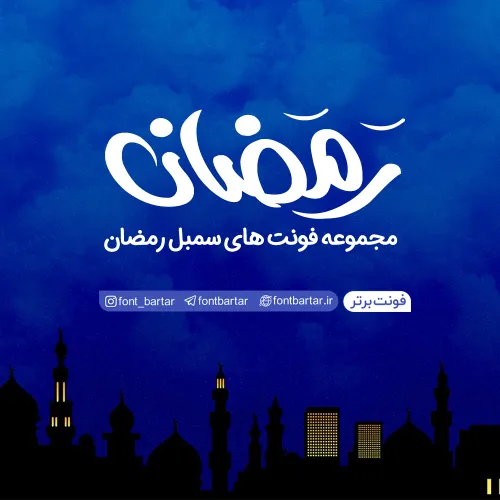
فونت سمبل رمضان
هم اکنون فونت و سمبل بسیار پر طرفدار و فوق العاده گرافیکی رمضان که شامل بیش از ۱۰۰ طرح زیبا از اسماء متبرکه مربوط به ماه مبارک رمضان است از فونت برتر در دسترس شما قرار می گیرد.
فونت سمبل رمضان مورد استفاده برای: